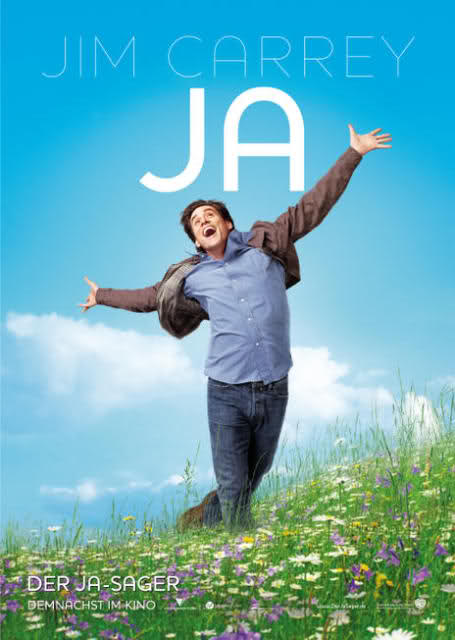
schrift von filmplakat gesucht
ich suche die schrift, die auf dem filmplakat für jim carrey’s film „ja“ verwendet wird:
passt soweit ich das auf anhieb sehe alles, nur das „A“ ist bei der houschka spitz und nicht rund.
ich hab die alternate gesehen, du hattest recht, es ist die houschka. vielen dank für die schnelle antwort!
ja, die hab ich inzwischen auch gefunden. nur war das erste ergebnis für houschka alternate. und da die houschka alternate ein spitzes a hat, war ich etwas irritiert.